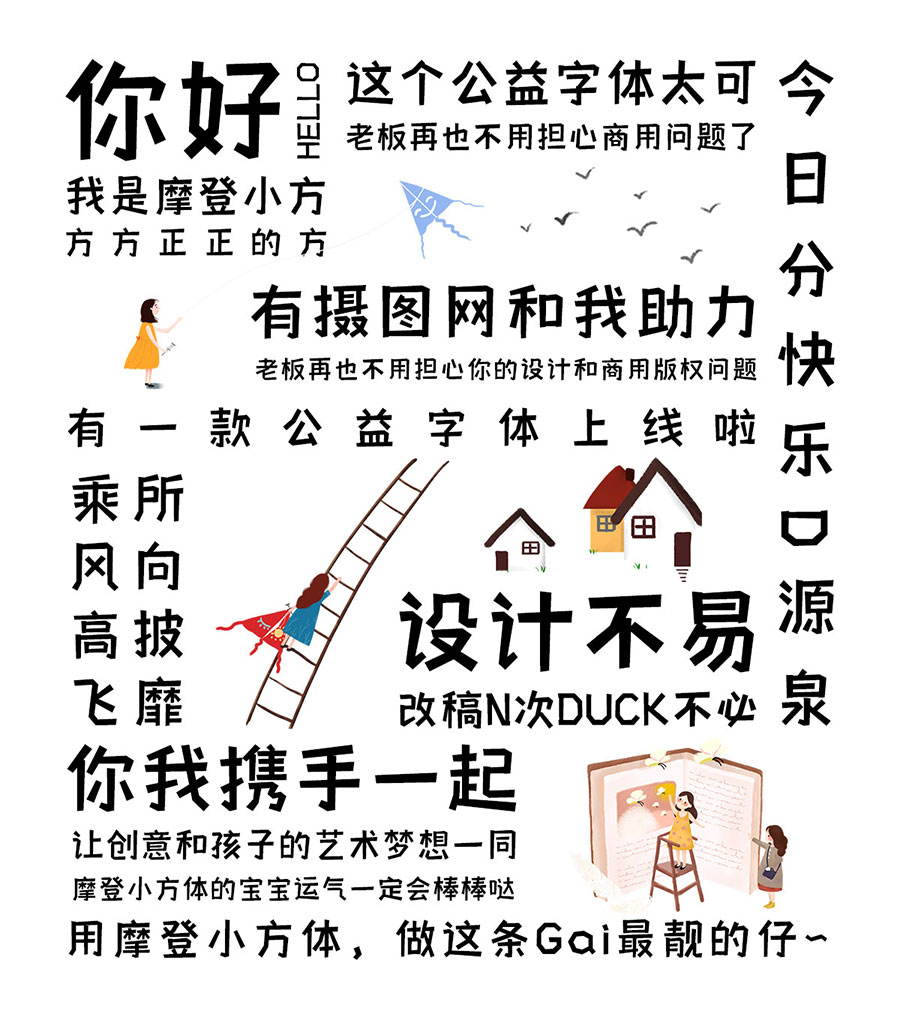
攝圖摩登小方體是攝圖網聯合國內專業字體設計機構iFonts共同推出的一款公益創意黑體字,攝圖摩登小方體作為一款創意黑體字,靈感來自未來空間的想象,傳達給人一種未來與現實的交際感。該字體筆畫整質而又不失靈氣活力,適中的字體筆畫粗度和幾何感的細節設計,讓字體有良好的視覺應用表現。通過對字體負形空間的處理,使字體整體感覺穩重端正而又不呆板,更加具有趣味性。適合電商、廣告、美食等商業宣傳和包裝設計,以及社交網絡的個性化用字。